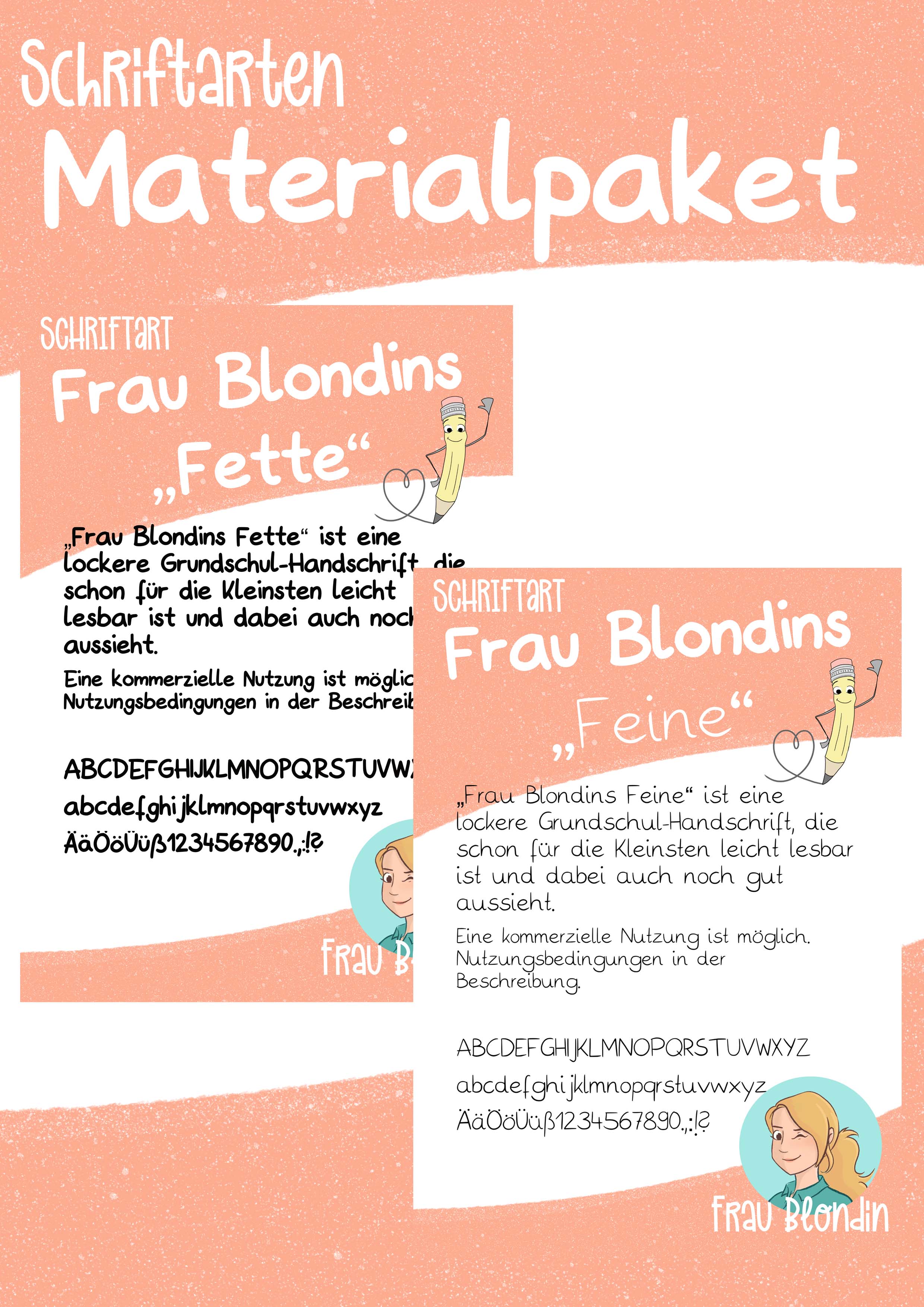
In diesem Materialpaket bekommst du meine beiden Schriftarten "Frau Blondins Feine" und "Frau Blondins Fette" im Bundle.
Dies ist eine von mir selbst erstellte Schriftart, die der Grundschrift ähnelt und schon von Kindern der ersten Klasse gut zu lesen ist. "Die Feine" besteht aus eher fein geschriebenen Buchstaben. Meine Schriftart "Die Fette" bildet die perfekte Ergänzung dazu. "Die Fette" ist ebenfalls hier auf eduki.de erhältlich.Die enthaltenen Buchstaben und Schriftzeichen sind auf dem Deckblatt angezeigt.Der Download enthält je eine .ttf und eine .otf -Datei. Mit dem Erwerb meiner Schriftart stimmst du meinen Nutzungsbedingungen zu. Eine ausführliche Version der Nutzungsbedingungen ist im Material enthalten.Durch den Kauf meiner Schriftart werden einfache, nicht-exklusive, inhaltlich eingeschränkte und personenbezogene Nutzungsrechte für den Käufer an der betroffenen Schriftart eingeräumt. Das bedeutet, meine Schriftart darf von dir als Käufer in Verbindung mit deinem selbst erstellten unterrichts- und schulbezogenen Material auch kommerziell genutzt werden, sofern folgende Vorgaben eingehalten werden:1.) Es handelt sich um von dir persönlich erstelltes unterrichts- bzw. schulbezogenes Material.2.) Das Material wird ausschließlich online zum Download über deine persönliche Webseite, deinen Blog und/oder die Verkaufsseiten eduki.com und/oder teacherspayteachers.com angeboten.3.) Dem von dir zum Verkauf angebotenen Unterrichtsmaterial muss eine gewisse geistige Tiefe zugrunde liegen. Das bedeutet, meine Schriftart darf dein Material unterstützen, aber nicht die alleinige Hauptkomponente des Materials bilden. Reine Buchstabenkarten o.ä. sind also nicht zur kommerziellen Nutzung freigegeben. 4) Füge bitte jedem Material, das meine Schriftart enthält, diesen Link hinzu: https://eduki.com/de/autor/453567/frau-blondin
Dies ist eine von mir selbst erstellte Schriftart, die der Grundschrift ähnelt und schon von Kindern der ersten Klasse gut zu lesen ist. "Die Fette" besteht aus fett geschriebenen Buchstaben. Meine Schriftart "Die Feine" bildet die perfekte Ergänzung dazu. "Die Feine" ist ebenfalls hier auf eduki.de erhältlich.Die enthaltenen Buchstaben und Schriftzeichen sind auf dem Deckblatt angezeigt.Der Download enthält je eine .ttf und eine .otf -Datei. Mit dem Erwerb meiner Schriftart stimmst du meinen Nutzungsbedingungen zu. Eine ausführliche Version der Nutzungsbedingungen ist im Material enthalten.Durch den Kauf meiner Schriftart werden einfache, nicht-exklusive, inhaltlich eingeschränkte und personenbezogene Nutzungsrechte für den Käufer an der betroffenen Schriftart eingeräumt. Das bedeutet, meine Schriftart darf von dir als Käufer in Verbindung mit deinem selbst erstellten unterrichts- und schulbezogenen Material auch kommerziell genutzt werden, sofern folgende Vorgaben eingehalten werden:1.) Es handelt sich um von dir persönlich erstelltes unterrichts- bzw. schulbezogenes Material.2.) Das Material wird ausschließlich online zum Download über deine persönliche Webseite, deinen Blog und/oder die Verkaufsseiten eduki.com und/oder teacherspayteachers.com angeboten.3.) Dem von dir zum Verkauf angebotenen Unterrichtsmaterial muss eine gewisse geistige Tiefe zugrunde liegen. Das bedeutet, meine Schriftart darf dein Material unterstützen, aber nicht die alleinige Hauptkomponente des Materials bilden. Reine Buchstabenkarten o.ä. sind also nicht zur kommerziellen Nutzung freigegeben. 4) Füge bitte jedem Material, das meine Schriftart enthält, diesen Link hinzu: https://eduki.com/de/autor/453567/frau-blondin